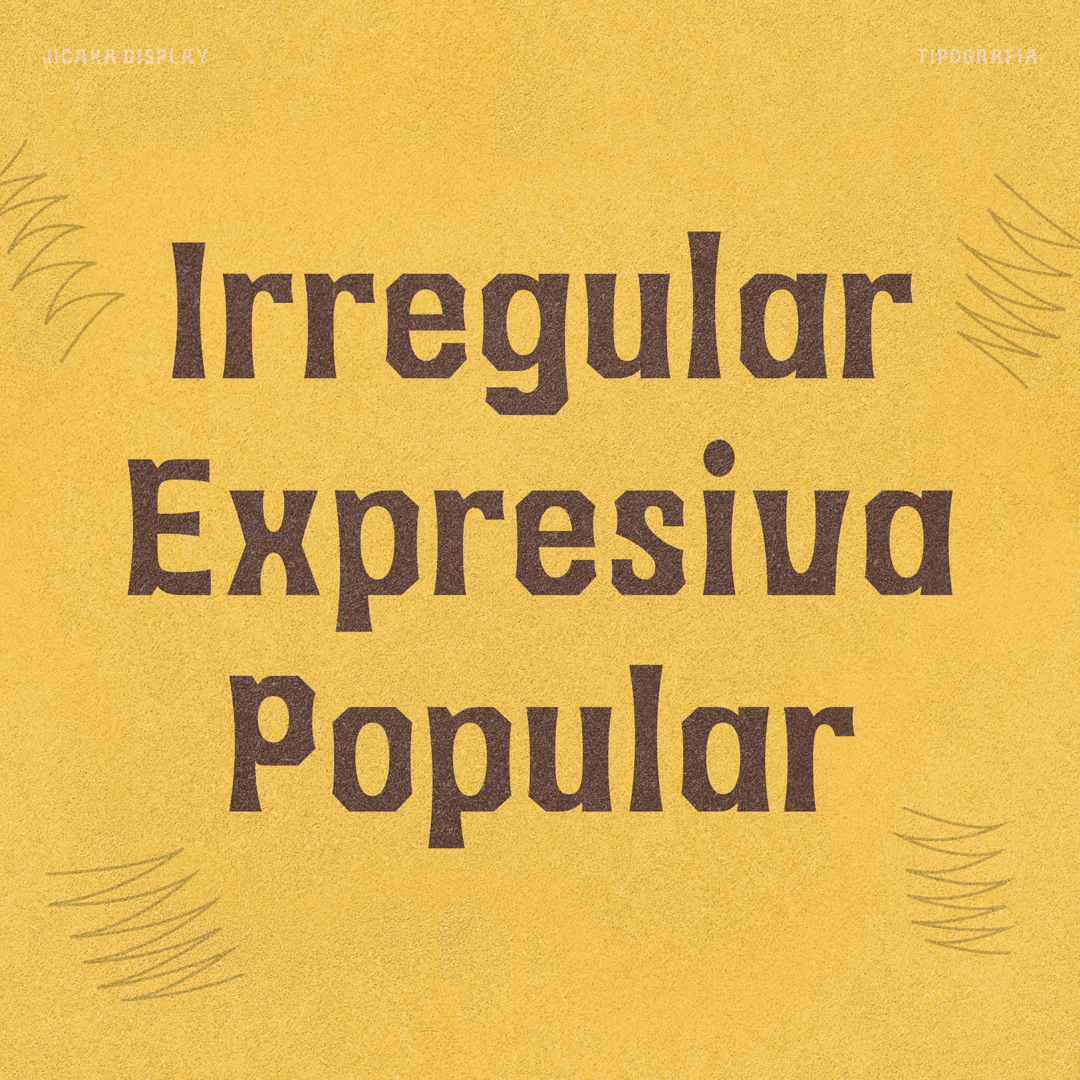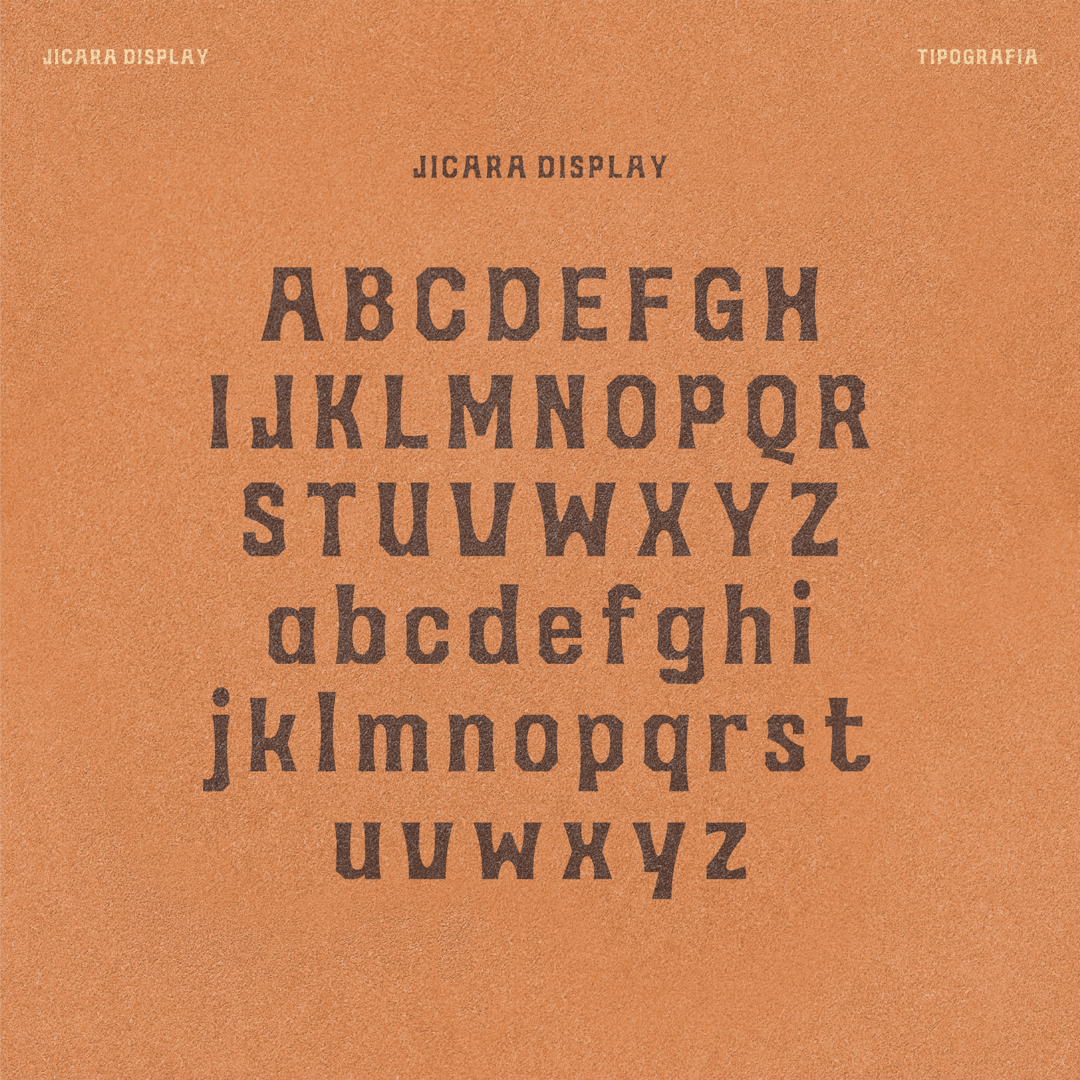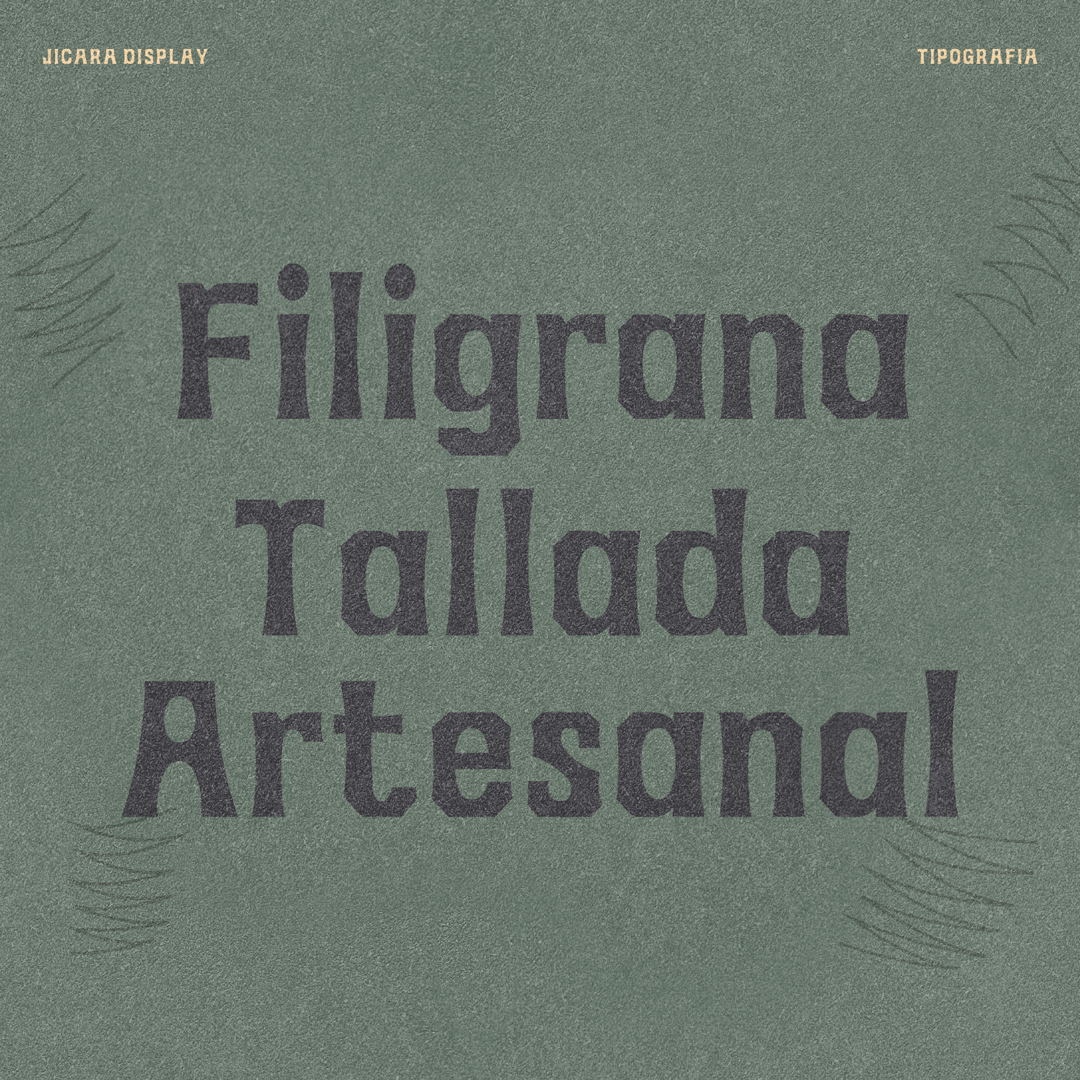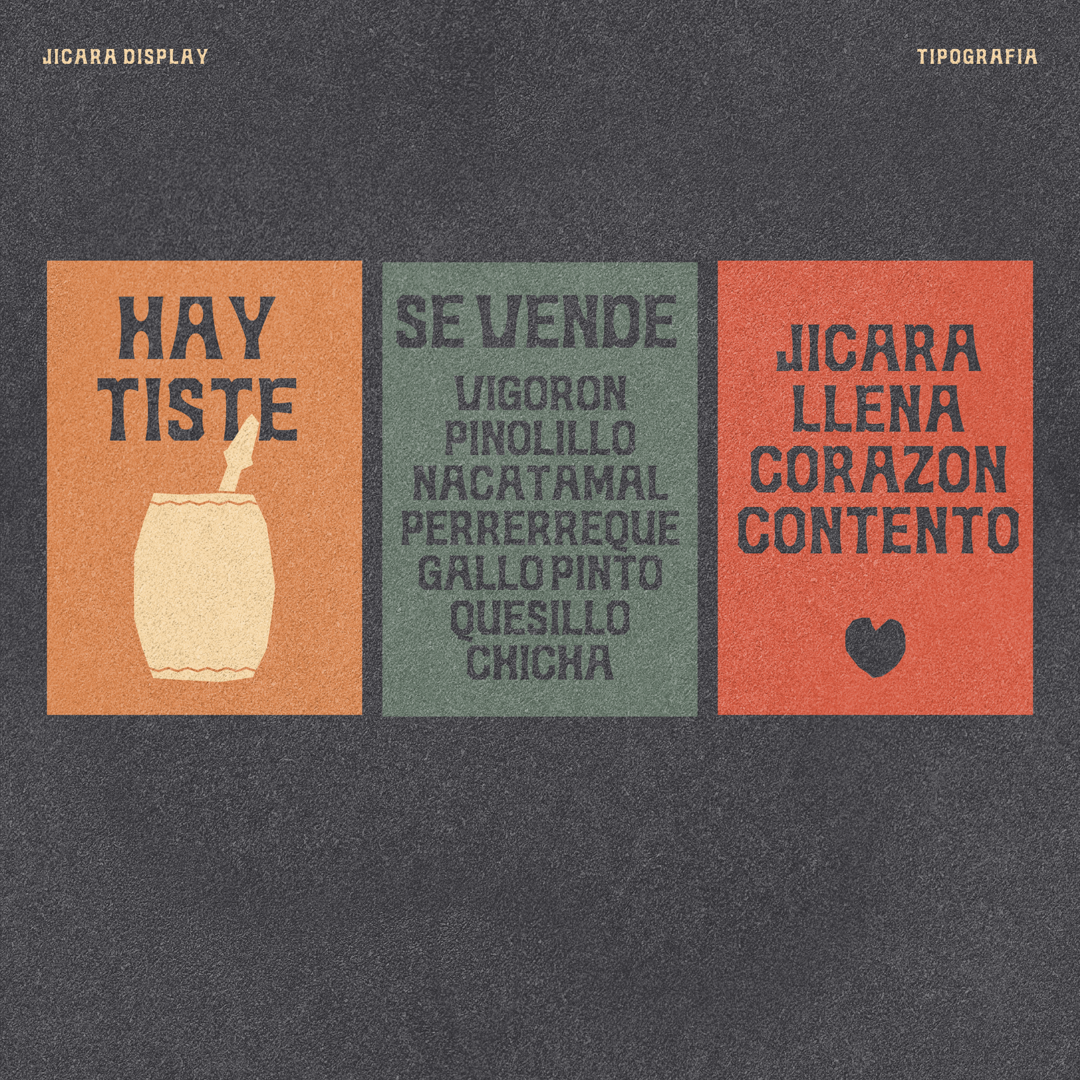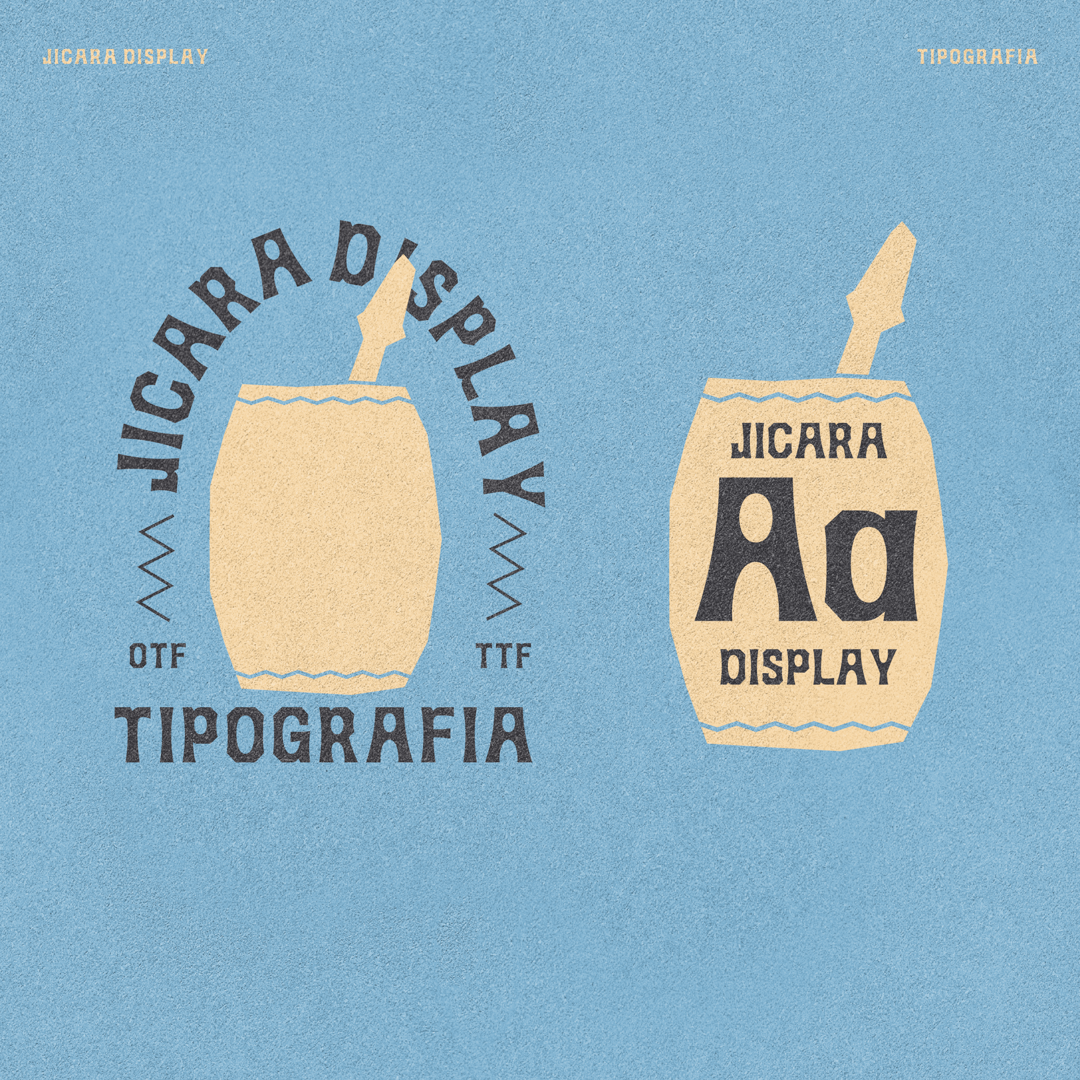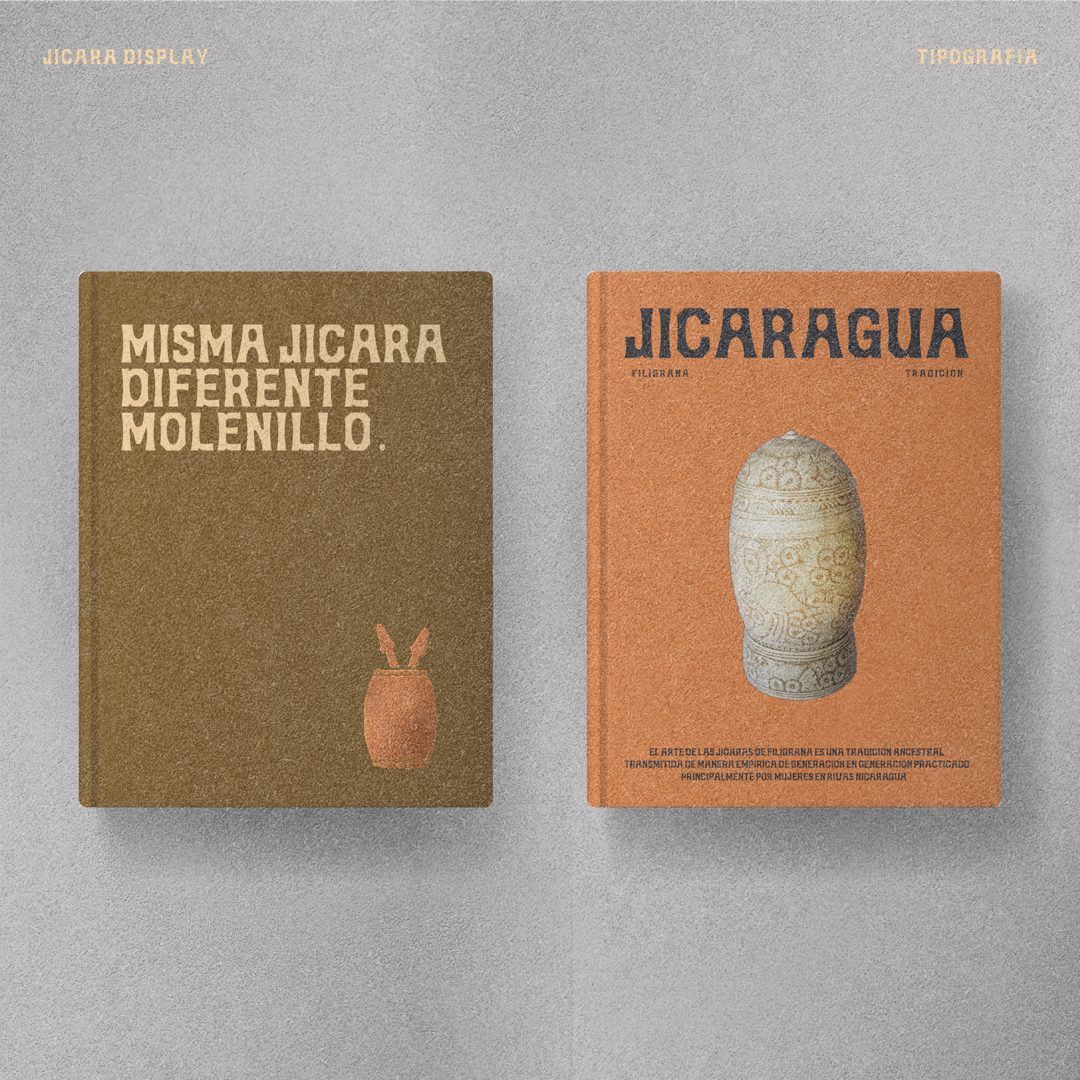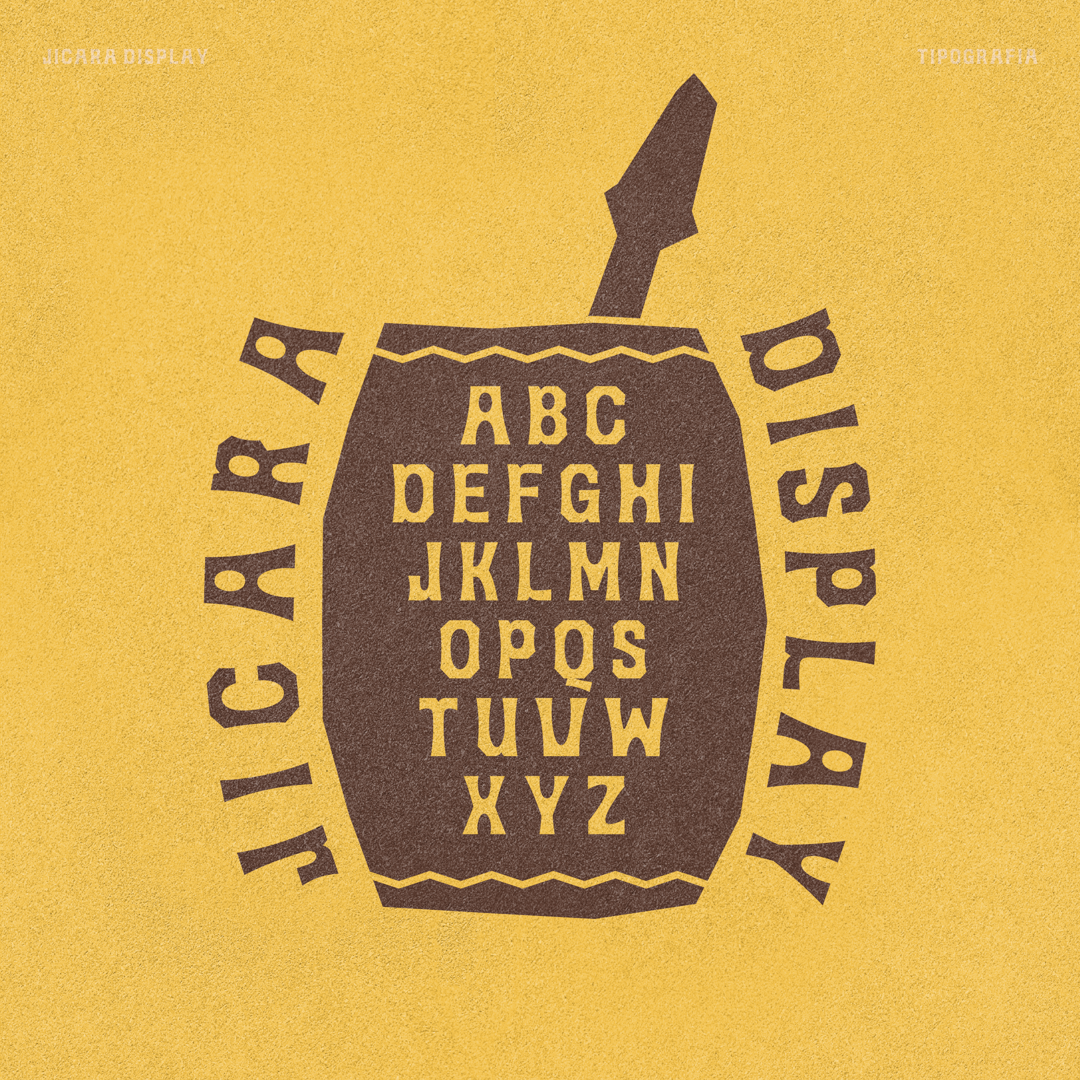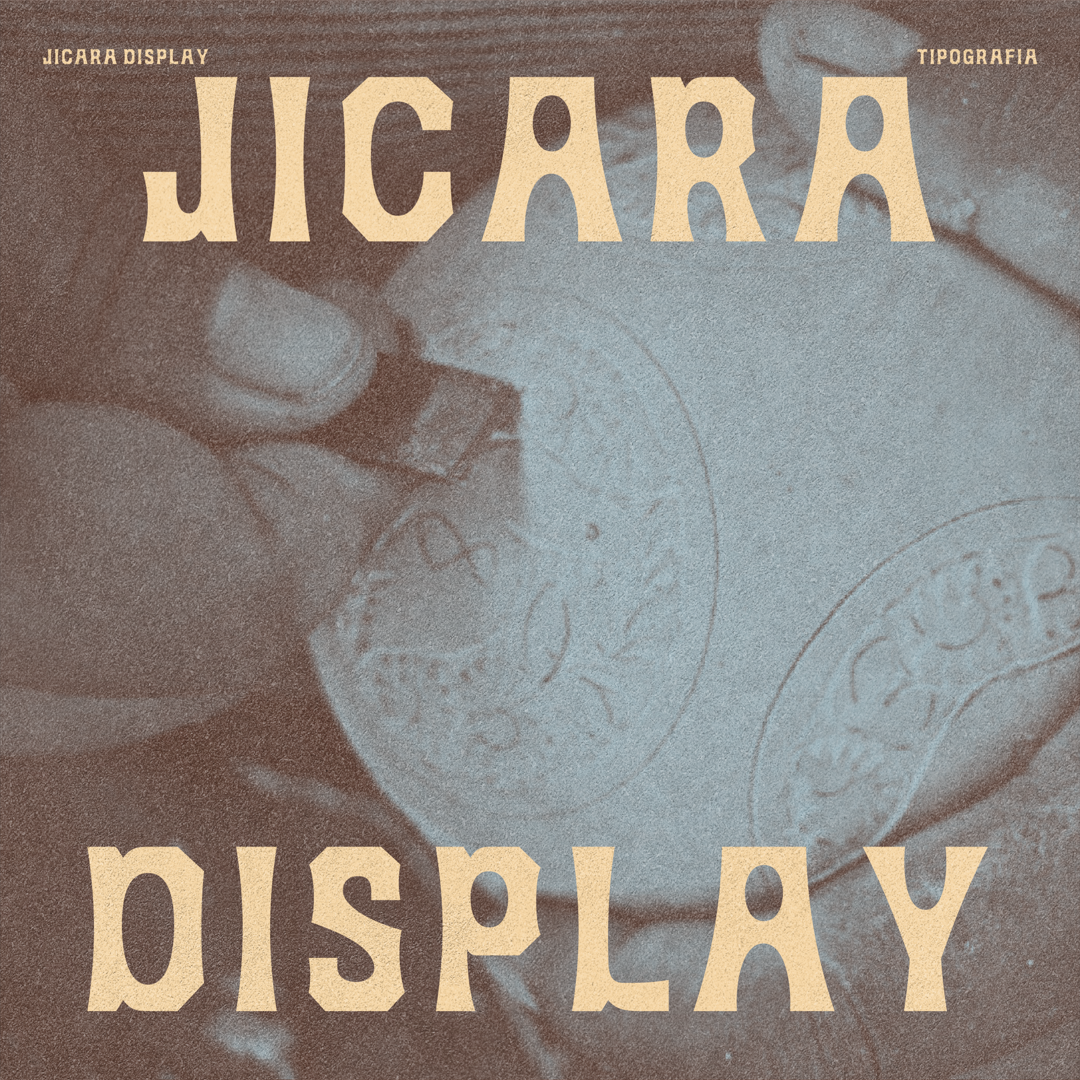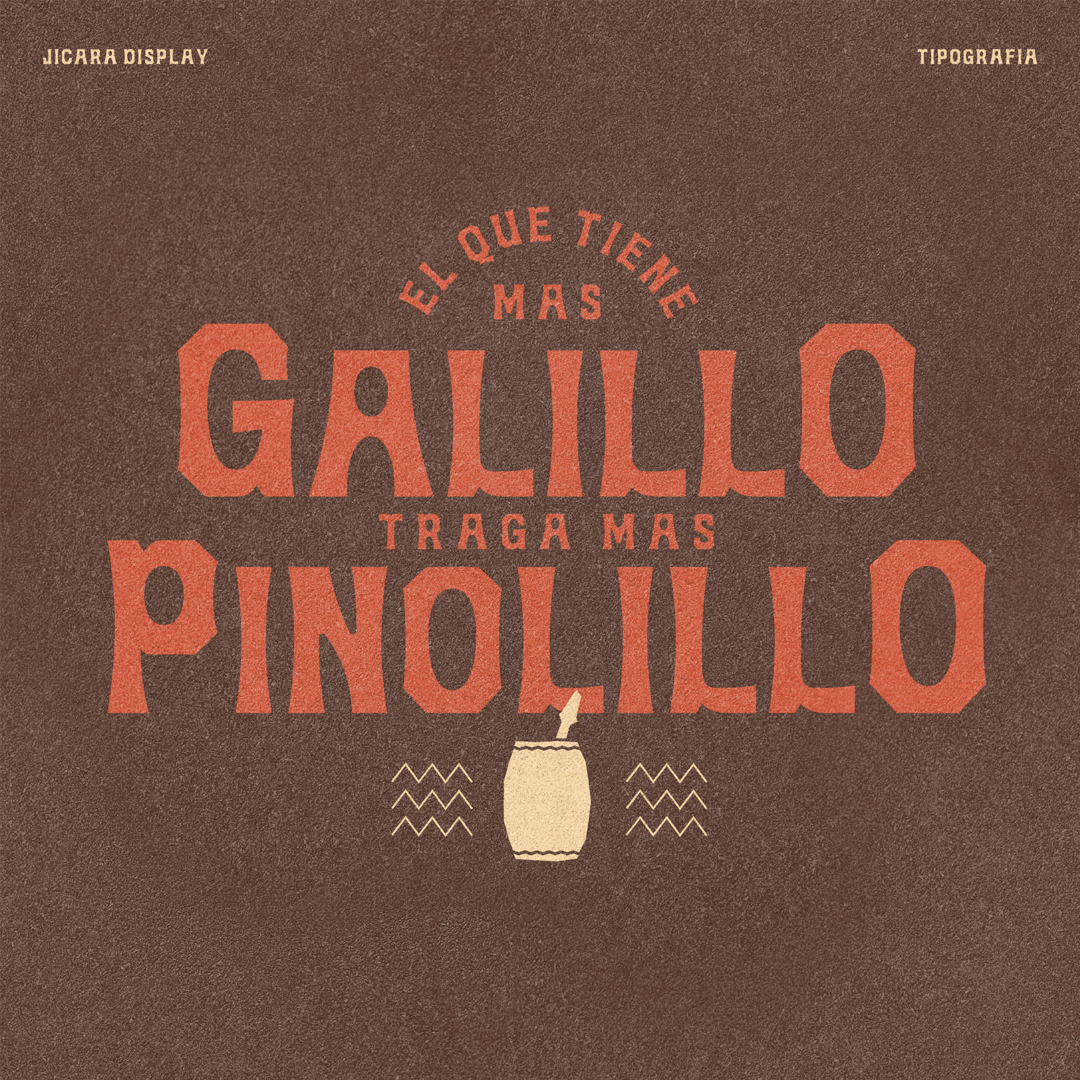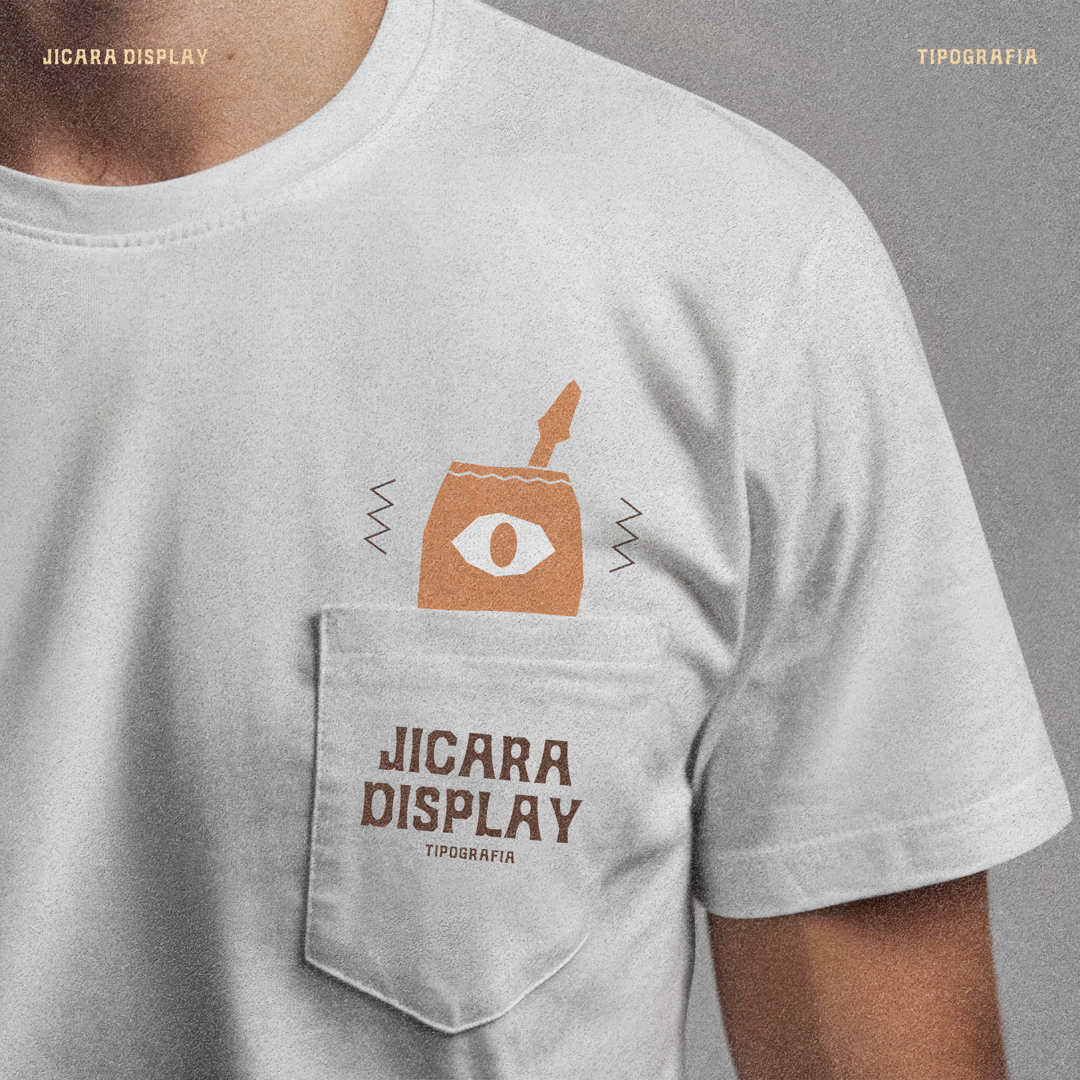
JICARA DISPLAY nace de la profunda admiración por el arte del tallado en jícaras de filigrana de Rivas, Nicaragua. Esta tipografía de estilo irregular y altamente expresivo captura la belleza imperfecta del tallado manual. Ideal para titulares y textos cortos que buscan presencia y carácter.
El proceso fue un recorrido por muchas fases, desde la conceptualización y la definición de la idea y atributos o “receta” de la tipografía. Durante esta etapa investigué mucho sobre el tema, a través de la información en internet, pero también consultándole a amistades que trabajan con artesanos. Luego de múltiples rondas de boceteado a mano, que me ayudaron a explorar opciones y hacer pruebas rápidas, logrando aclarar aún más las ideas. Después de llegar a un boceto más o menos claro de los caracteres de control, siguió la etapa de construcción digital, en la que me enfrenté por primera vez y más a fondo con Glyphs; en esta etapa tuve mucho tiempo para familiarizarme con la aplicación porque tuve que trabajar múltiples iteraciones y rondas de ajustes.
Lejos de ser perfecto, el proyecto continúa en beta. Fue un proyecto en el que me “disfrustre” un montón, pero aprendí mucho y quedé con muchas ganas de aprender más.